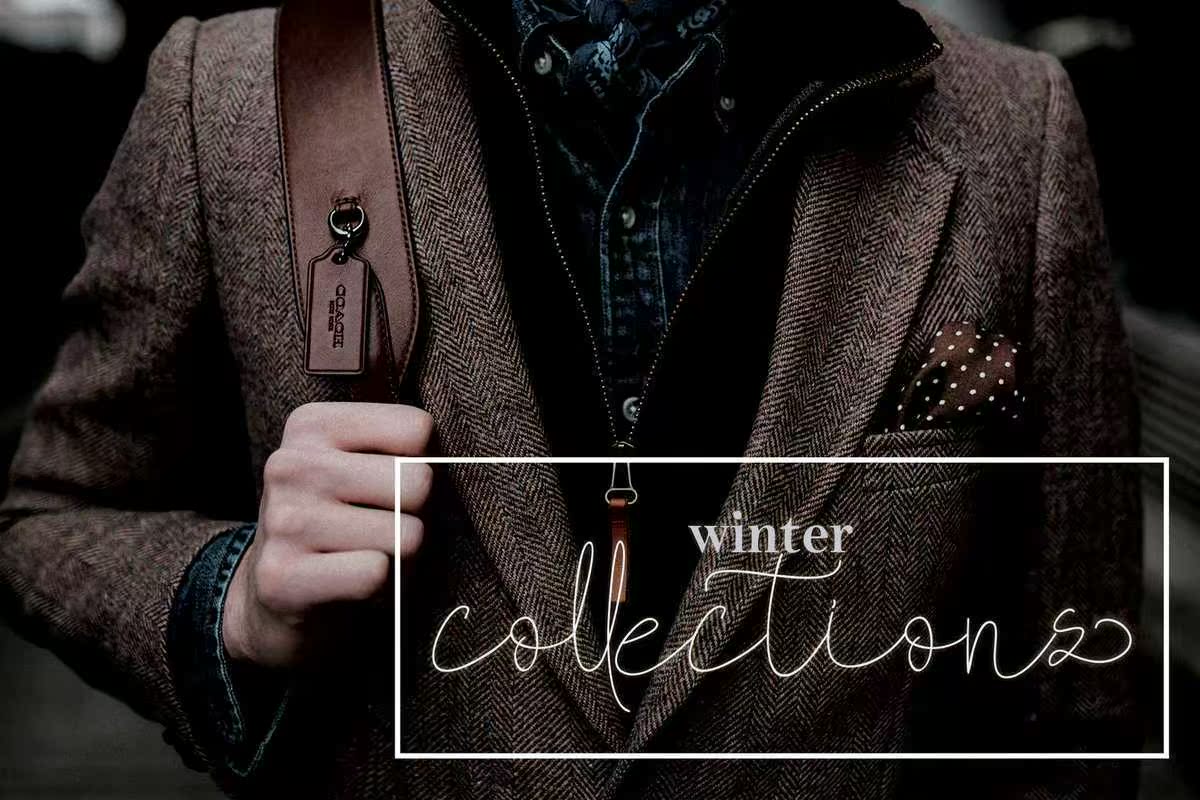
马利诺单线-手写体免费字体免费手写体 15830
MallinoMonoline是一种签名,您可以使用它来进行商标设计、posterheadline、杂志、书名、名片、美容设计、广告、产品设计、婚礼宣传、签名或书写报价。MallinoMonoline是一种签名,您可以使用它来进行商标设计、posterheadline、杂志、书名、名片、,美化广告、广告、产品设计、婚礼庆典、签名或书面报价。